Выбор идеального шрифта — это один из самых важных этапов при создании любого дизайн-проекта. В нашей подборке мы рассмотрим 10 лучших шрифтов, которые вы сможете использовать в своих дизайн-проектах абсолютно бесплатно.
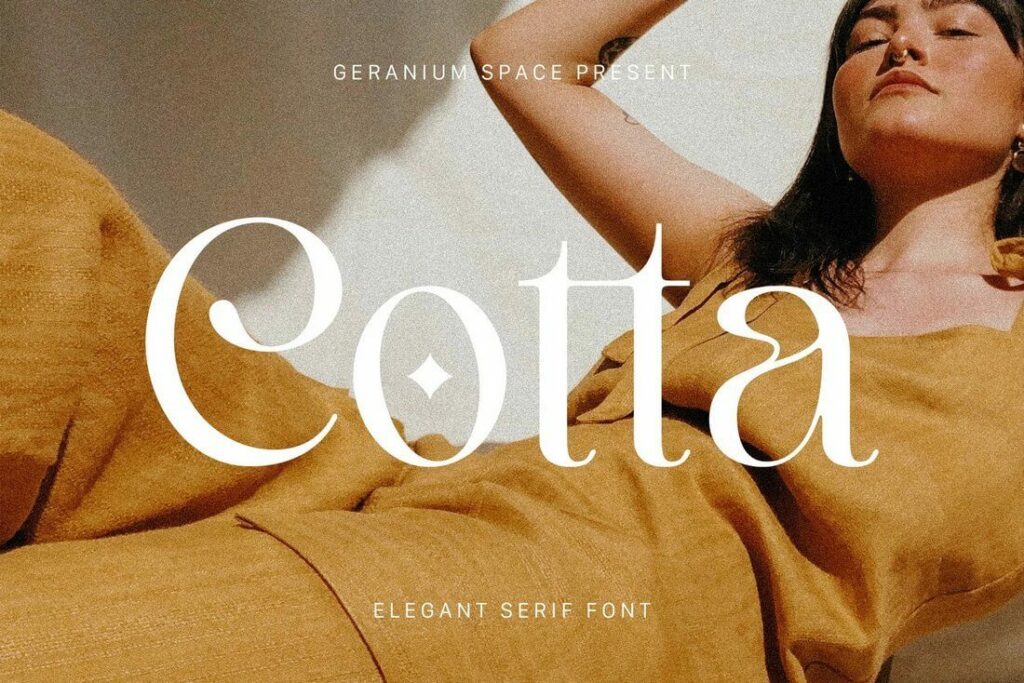
Cotta — это один из лучших бесплатных шрифтов с засечками, которые вы найдете в нашей подборке. У него выдержанный и элегантный дизайн букв с красивыми и изящными изгибами. Этот шрифт можно использовать бесплатно в личных и коммерческих проектах.
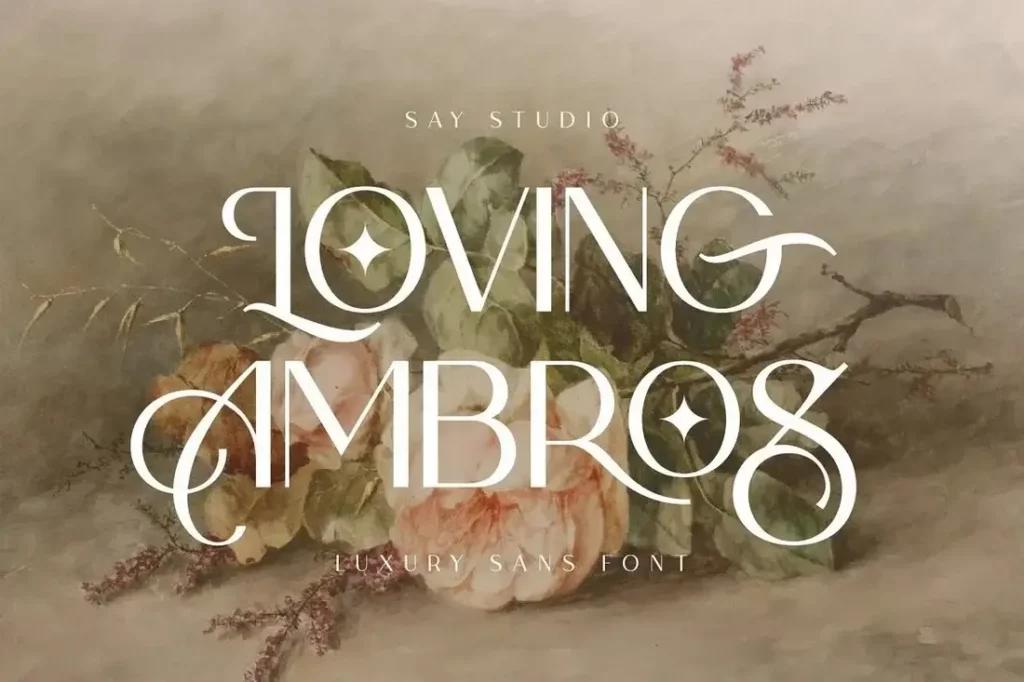
Если вы ищете еще более экстравагантный, но в то же время элегантный шрифт, то мы советуем вам Loving Ambros. Этот шрифт сочетает в себе стиль рукописного шрифта с засечками. Вы можете использовать его бесплатно в личных проектах.
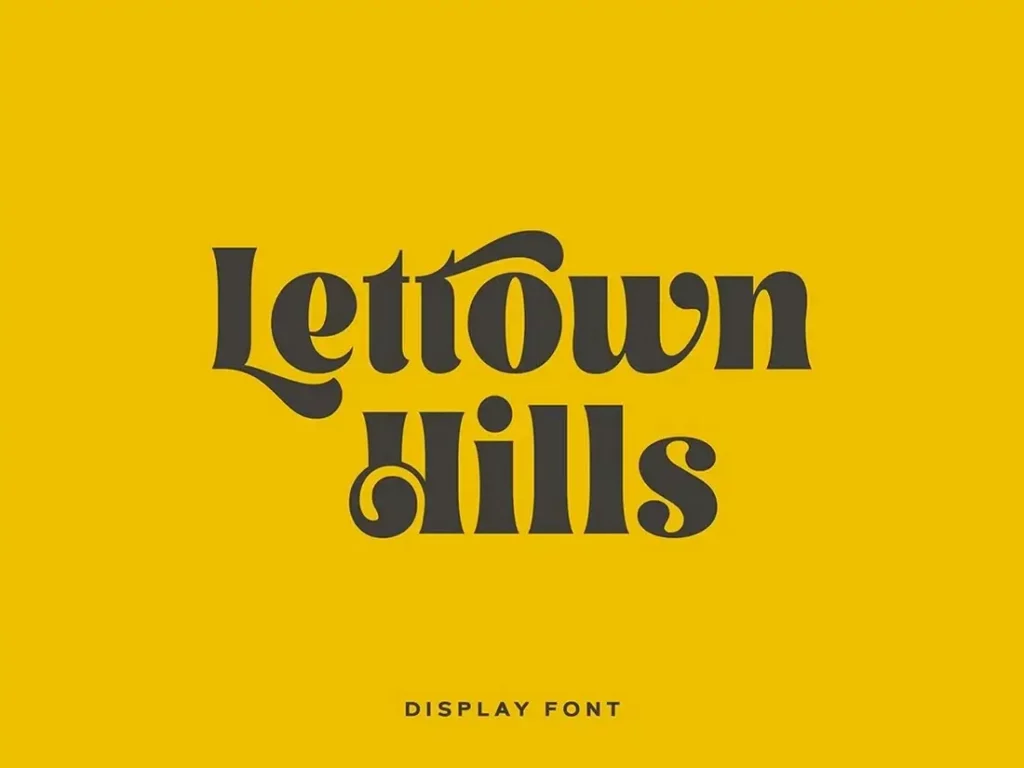
Этот стильный и необычный дисплейный шрифт идеально подойдет для создания красивых логотипов, этикеток и заголовков веб-сайтов. Шрифт можно бесплатно загрузить и использовать в личных проектах.
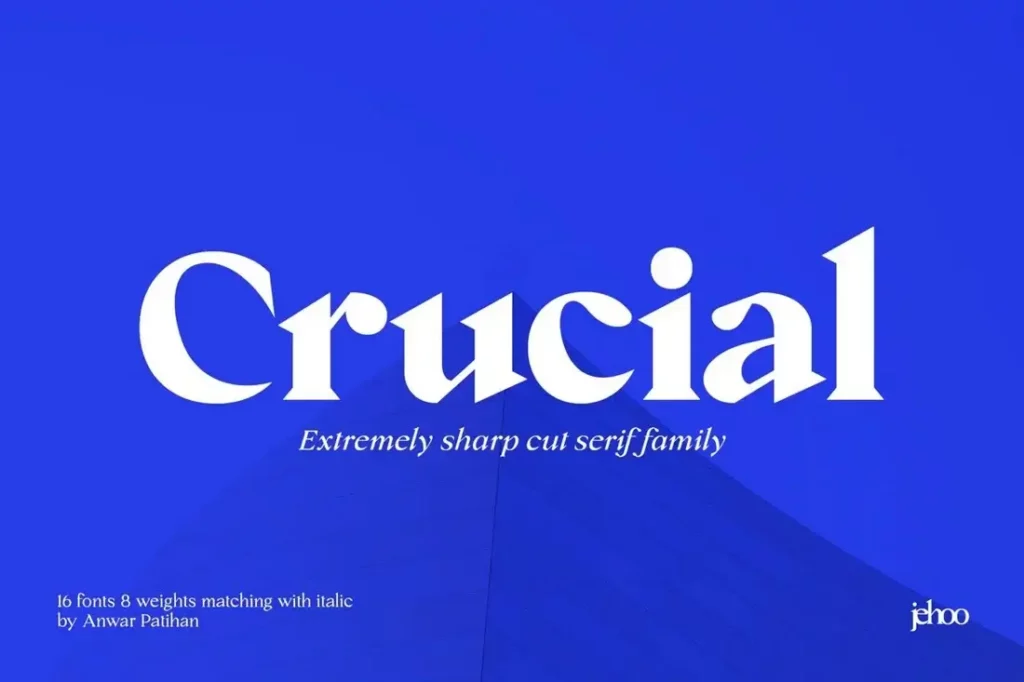
Crucial — это строгий и элегантный шрифт, который идеально подойдет для всех ваших профессиональных дизайнерских проектов. Особенно хорошо он будет смотреться в дизайнах для крупных брендов и корпоративного бизнеса. Версии шрифта со средним и курсивным начертанием можно бесплатно использовать в коммерческих проектах.
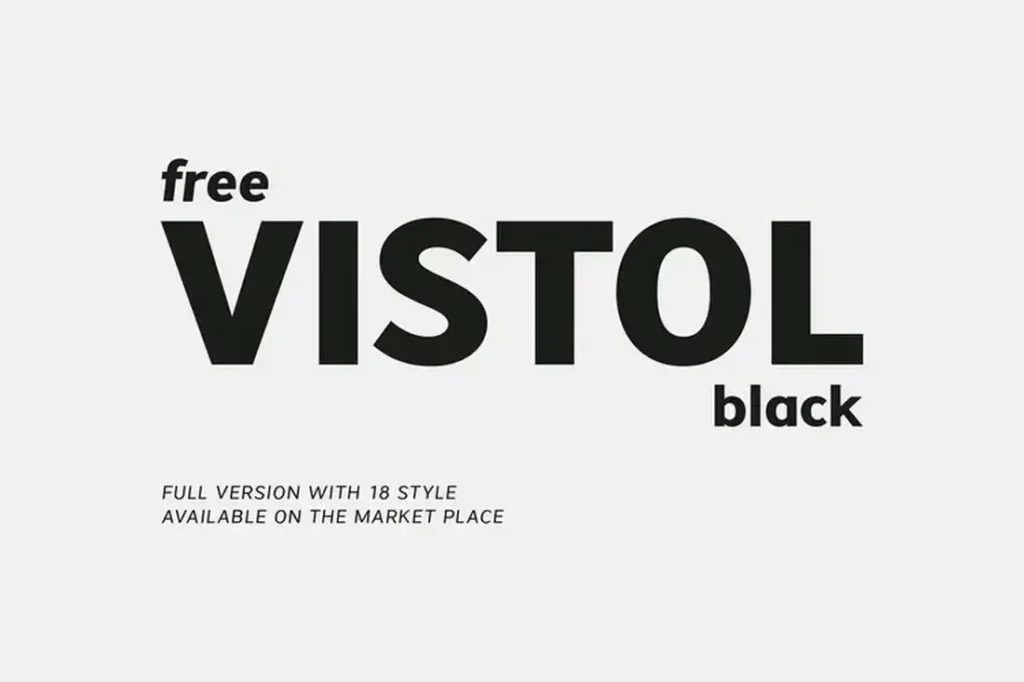
Vistol Black — это современное семейство шрифтов без засечек, которое состоит из 18 различных шрифтов. У Vistol Black строгий и прямой дизайн букв, который идеально подходит для профессиональных проектов. Вы можете скачать бесплатную версию шрифта, чтобы использовать ее в личных и коммерческих проектах.
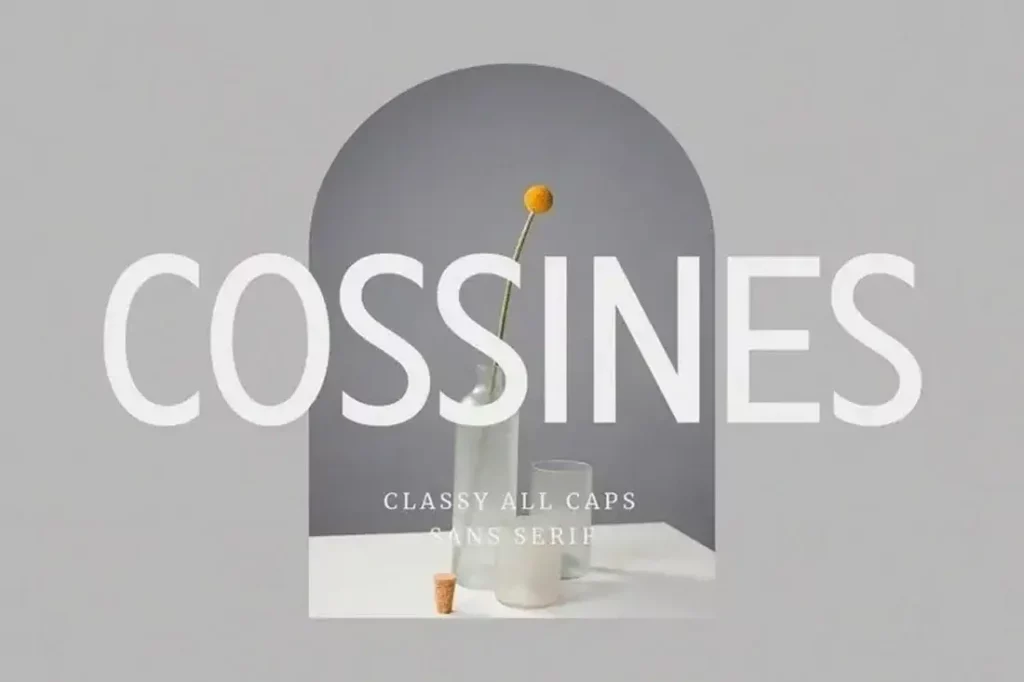
Cossines — это шрифт, который полностью состоит из заглавных букв. Вы можете с легкостью использовать его для создания заметных и привлекательных заголовков для своих веб-проектов. Этот шрифт также доступен для бесплатного использования в ваших личных проектах.